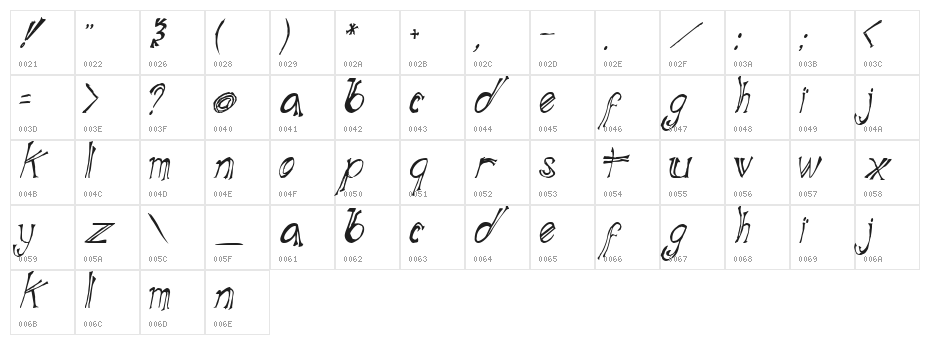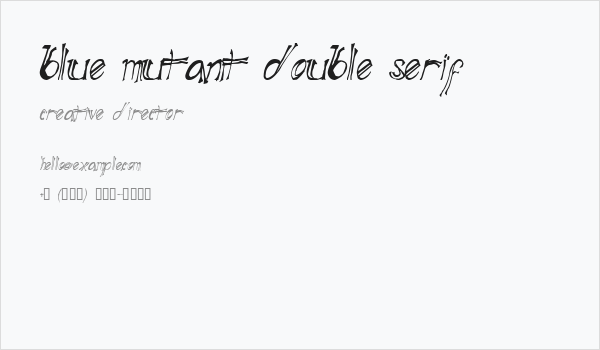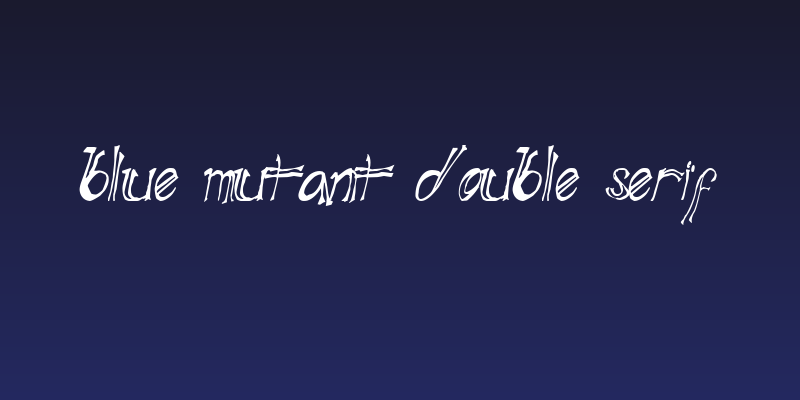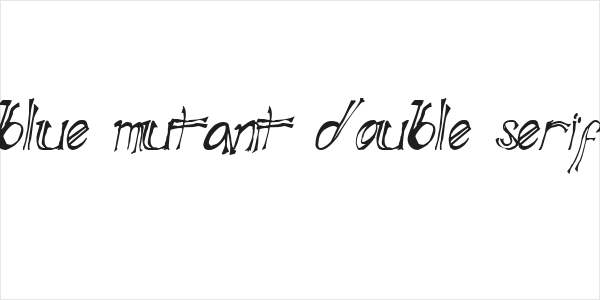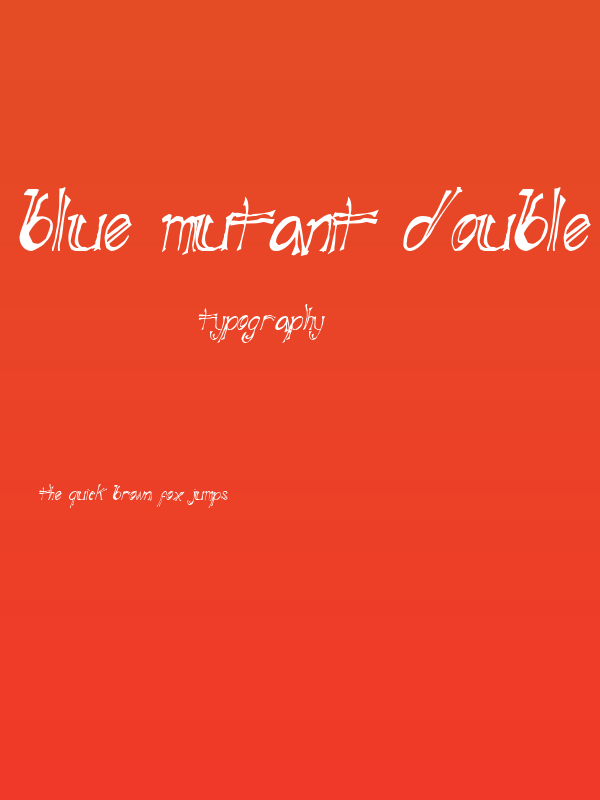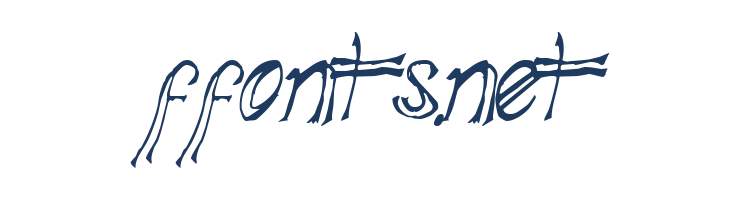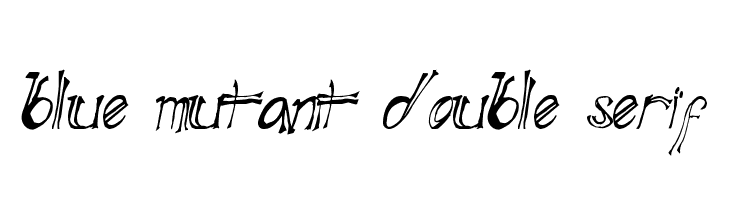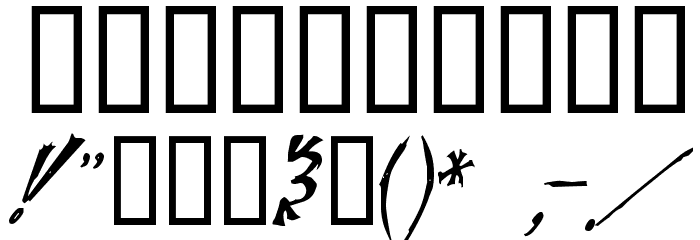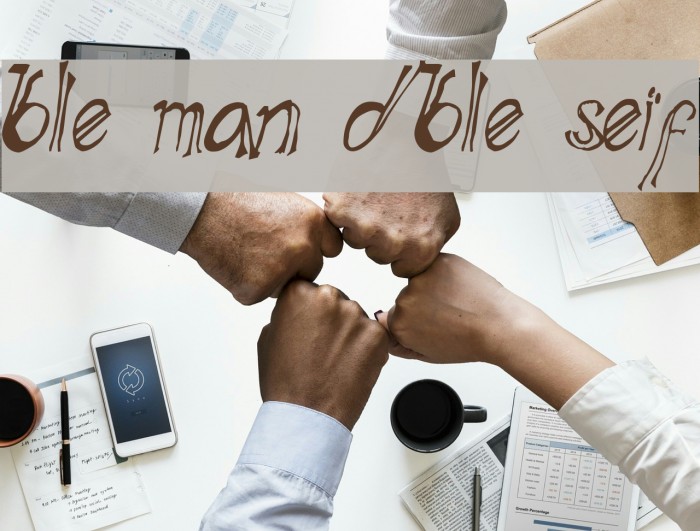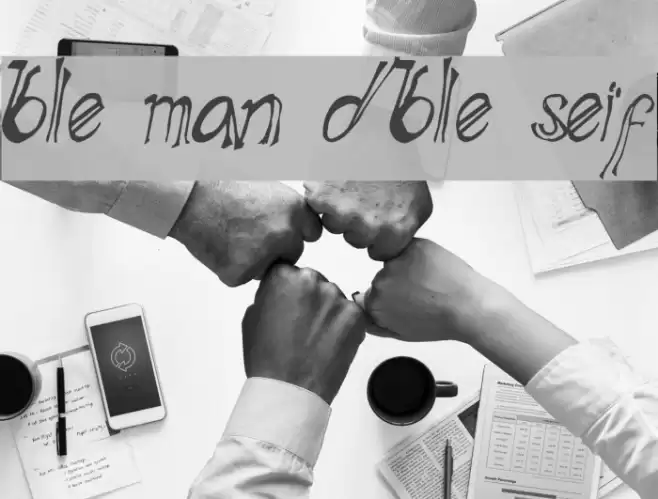
Blue Mutant Double Serif Font
| مشاريع مقترحة | Ideal for album covers, posters, and creative branding projects that require a bold and unconventional typeface. |